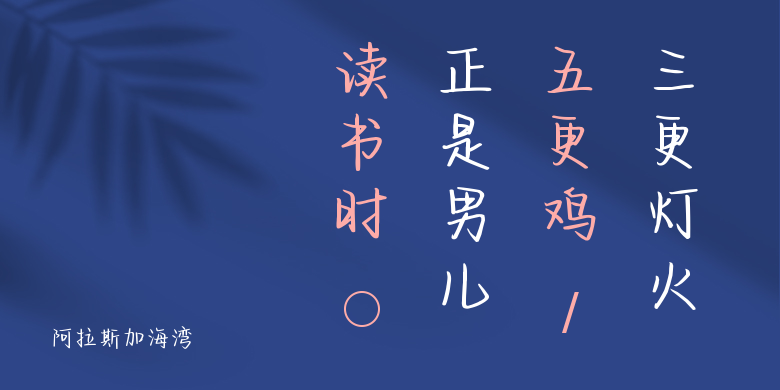
阿拉斯加海湾
阿拉斯加海湾,这款字体结构工整、笔画清晰,兼顾美观与易读性,适用于标题、正文、海报、包装、LOGO 等多种场景。字形优雅稳定,风格百搭耐看,适配日常排版与创意设计,让文字呈现更舒适、更具质感。阿拉斯加海湾一笔一画,皆是细节,以均衡的比例、流畅的线条打造舒适视觉体验,字形端正大气,风格简约现代。无论是商业设计、品牌宣传还是日常排版,都能轻松驾驭,让文字更有格调与力量。阿拉斯加海湾字体下载。